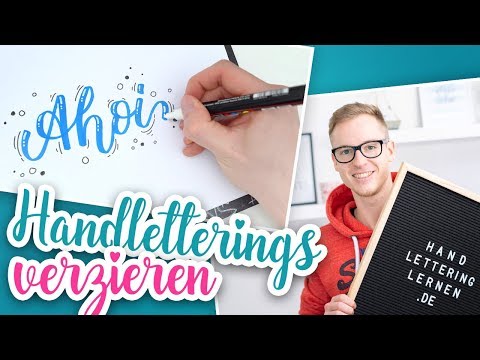
Dekoelemente und Verzierungen geben jedem Handlettering den letzten Schliff. Sie sorgen für die nötigen Details und machen deinen Schriftzug lebendig.
In diesem Artikel erfährst du, worauf du bei der Verzierung deiner Letterings achten solltest und welche typischen Techniken und Dekoelemente du nutzen kannst.
Arten der Verzierung
Bei der Verzierung und Dekoration deiner Handlettering gibt es drei verschiedene Herangehensweisen.
1. Verzierung innerhalb der Buchstaben
Die direkte Verzierung in bzw. auf der Schrift. Zum Beispiel durch Punkte oder andere Muster. Auch Verläufe oder Lichtreflexe gehören dazu. Dabei bewegst du dich wirklich nur innerhalb der Linien deiner Buchstaben.
2. Verzierung an den Buchstaben
Die zweite Möglichkeit ist die Verzierung direkt an den Buchstaben. Dazu gehören zum Beispiel Konturlinien, Schatten, 3D-Effekte oder andere Techniken, die außerhalb der Buchstaben angewendet werden.
3. Dekoration durch zusätzliche Elemente
Schließlich gibt es noch die Dekoration mit Hilfe zusätzlicher Elemente. Also zum Beispiel kleine (oder große) Symbole, Kreise, Striche usw. Auch gemalte Motive gehören in diese Kategorie.
Den Inhalt unterstreichen
Ich bin ein großer Fan davon, die Verzierungen zu nutzen, um den Inhalt meines Letterings zu stützen. Natürlich beginnt diese Herangehensweise bereits bei der Wahl der richtigen Schrift. Danach lässt sich der Inhalt aber zusätzlich stützen.
Bei einem Handlettering zum Thema Natur versuche ich, organische Formen zu nutzen. Außerdem nutze ich Schmuckelemente wie Blätter, Blumen, Steine, Wolken und ähnliche natürliche Elemente.
Das gilt übrigens auch für echte Dekoration, die ich gern für Fotos meiner Letterings nutze.
Ist der Inhalt eher kühl und technisch ergänze ich den Schriftzug lieber mit kantigen Elementen. Zum Beispiel Bruchstücke, scharfe Formen und spitze Linien.
Und wenn es um Harmonie und Liebe geht, dann sind natürlich kleine Herzen das Symbol der Wahl!
Was ist zu viel?
Wichtig beim Einsatz von Verzierungen ist die richtige Balance zu finden. Einerseits möchtest du deinen Schriftzug hervorheben und in Szene setzen, andererseits soll die Schrift der Protagonist deines Kunstwerks bleiben.
Verwendest du zu viel Dekoration tritt dein Lettering eventuell in den Hintergrund und wird die schönen Formen und Schnörkel werden kaum mehr wahrgenommen.
Versuche also stets einen schönen Kompromiss zu finden – je nach dem, welches Ziel du mit deinem Handlettering verfolgst.
Verzierungen für dich
Ich möchte dir auf dieser Seite noch einige Techniken demonstrieren, die du für deine eigenen Letterings einsetzen kannst. Dazu nutze ich ein einfaches, unverziertes Handlettering, an dem ich die verschiedenen Techniken beispielhaft demonstrieren werde.
So sieht das Lettering ohne jegliche Verzierung oder Dekoration aus:
In der Galerie findest du nun verschiedene Techniken zur Verzierung und Dekoration.
Schau dir an, wie unterschiedlich die einzelnen Techniken wirken und wie sie die Optik des Schriftzugs verändern. Die volle Wirkung entfalten sie außerdem erst in Kombination.
Verzierungen im Video
Bereits vor längerer Zeit habe ich zu diesem Thema auch ein Video gemacht. Schau mal rein, wenn du die einige Techniken noch einmal in Bewegung sehen möchtest.